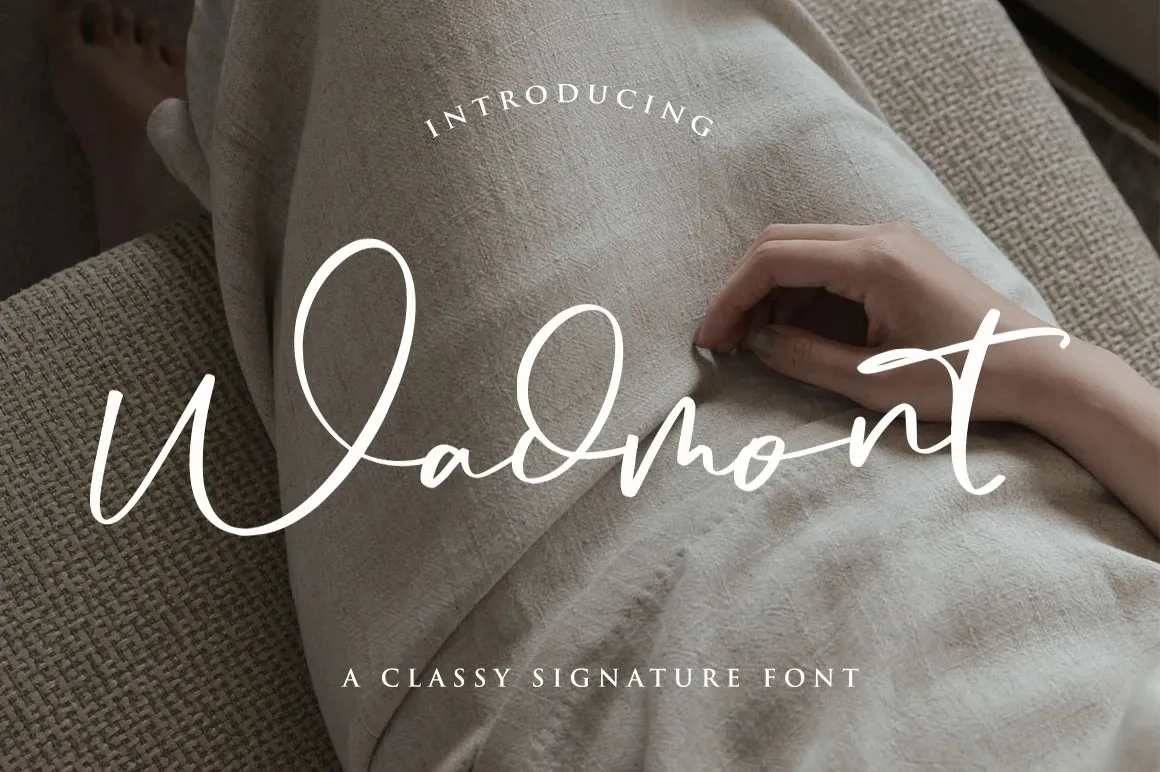
A Wadmont Font é uma elegante assinatura para letras modernas e sofisticadas criada pela Vultype Co. Com diferentes espessuras e um gesto encantador, ela se destaca como uma excelente adição aos designs que buscam incorporar o charme de escrita contemporânea, recheado com ligaduras e estilos alternativos para dar um toque único e vibrante ao design. Esta fonte é perfeita tanto para criações modernas quanto para trabalhos mais tradicionais, proporcionando aos designers uma ferramenta versátil que pode ser usada em variedades de projetos, desde logotipos até letras do corpo do texto. Seja você um designer ou um aficionado pelo design gráfico, a Wadmont Font é uma escolha inteligente para incorporar ao seu kit, adicionando elegância e originalidade a qualquer projeto que desenvolva.